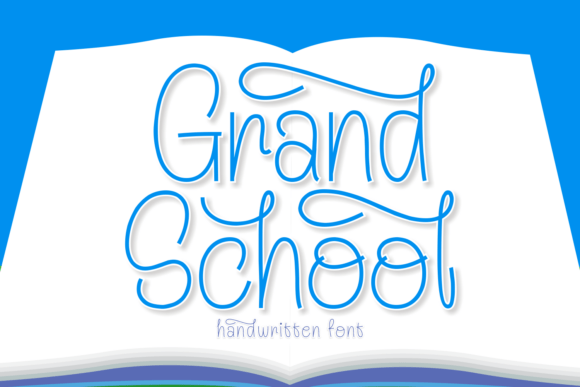
Grand School
適切なデザイン要素を見つけるのは難しい場合がありますが、Grand Schoolは作品を即座に引き立てる優れたコレクションを提供します。
POD(オンデマンド印刷)製品、結婚式の招待状、またはソーシャルメディアのグラフィックを作成している場合でも、Grand Schoolは理想的です。